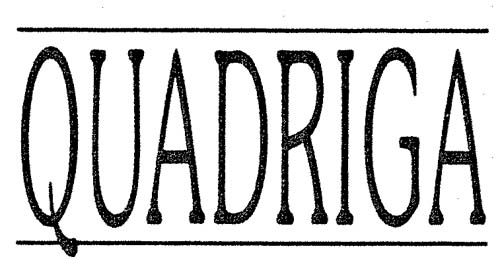
mein Vater hat mich gefragt, welche Schrift das ist, da ich keine Ahnung habe, dachte ich frage mal hier nach.
Stammt von einer Visitenkarte, Schrift ist wesentlich enger (condensed ???) als "normal".
Ich höre die Buchstaben stöhnen und jaulen. Klarer Fall von Buchstabenquälerei! :evil:
Souvenir! Natürlich, jetzt fällt es mir wie Schuppen ...
Wusste ich doch, dass ich dieses Stimmchen kenne: "Ich bin ein Font, hol mich hier raus!"